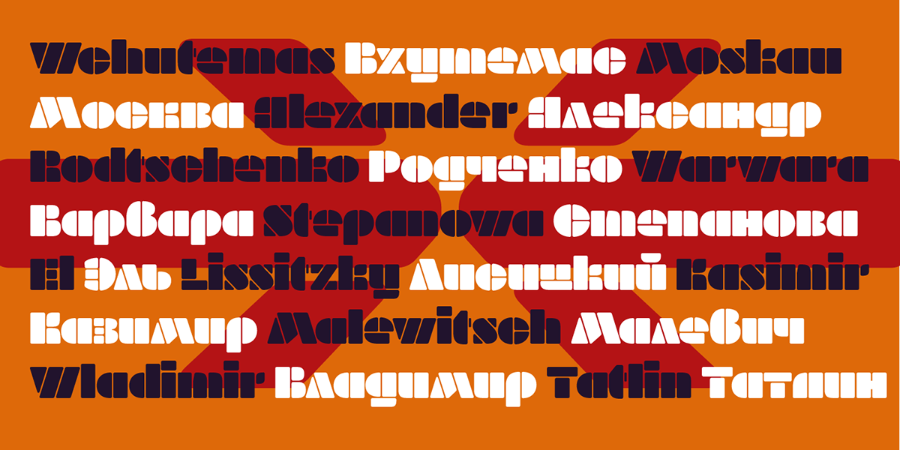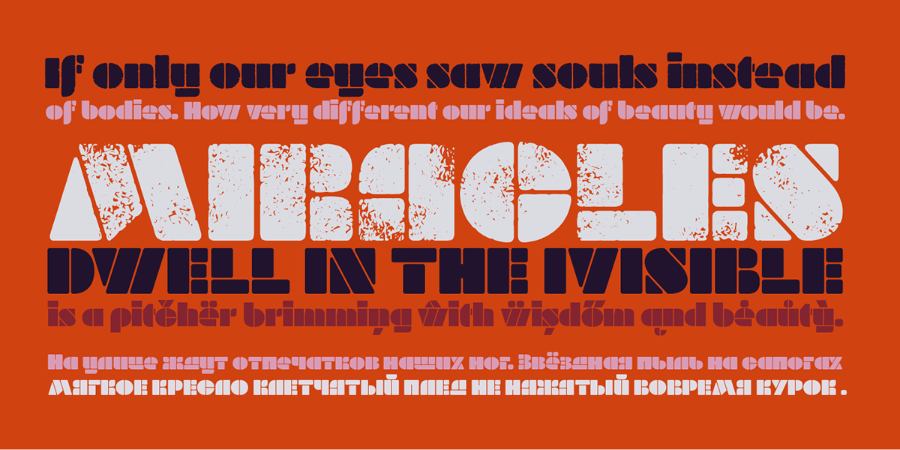
Milka字体家庭免费演示
Milka字体家庭免费演示是由在近70年期间出生的设计师队创造的8样式stencil字体家庭的部分。这是一个由着名的保加利亚艺术家Milka Peikova于1979年设计的字母数字扩展。米尔卡的基本是一个干净的模板设计字体。老年,烤,脆,脆,干和软的风格是受模板和凸版技术的启发。但更重要的是,米尔卡通过增加不同程度的温暖或粗糙来扩大有用性。因此,这种字体将看起来不错,作为标识或图标。